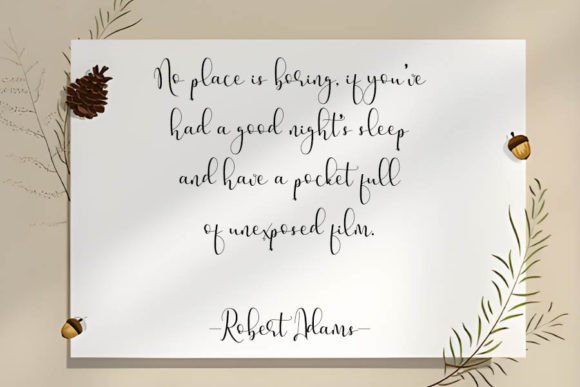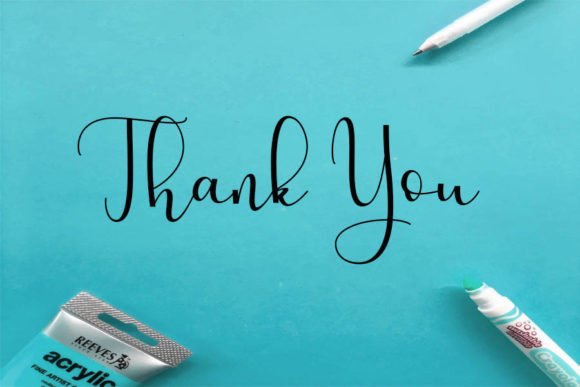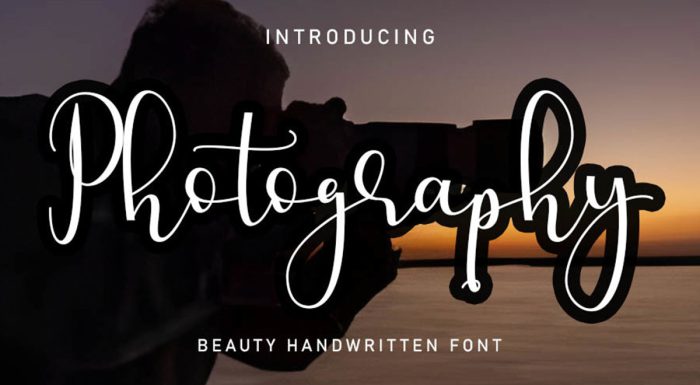
فونت Photography انگلیسی
فونت Photography، با خطوط نرم و خوشنویسی خاص خود، انتخابی ایده آل برای پروژه هایی است که نیازمند ظرافت و زیبایی هستند. این فونت، حسی از هنر عکاسی و ثبت لحظات ماندگار را به مخاطب القا می کند و به همین دلیل، برای طراحی لوگو، کارت ویزیت، وبسایت های مرتبط با عکاسی، آلبوم های عکس و حتی نوشته های کوتاه در شبکه های اجتماعی بسیار مناسب است.
یکی از ویژگی های برجسته Photography، خوانایی بالای آن است. با وجود ظرافت و پیچیدگی های خاص در طراحی حروف، این فونت در اندازه های مختلف به خوبی خوانده می شود و چشم را خسته نمی کند. این ویژگی، به ویژه در طراحی های دیجیتال که اندازه متن ممکن است متغیر باشد، اهمیت زیادی دارد. همچنین، تنوع وزن های مختلف این فونت، دست طراح را برای استفاده در موقعیت های گوناگون باز می گذارد. از متن های بولد برای عناوین گرفته تا متن های ظریف تر برای توضیحات، Photography به خوبی پاسخگوی نیازهای مختلف است.
البته باید به این نکته هم اشاره کرد که شاید این فونت برای متن های بسیار طولانی و کتابی مناسب نباشد، زیرا تمرکز آن بیشتر بر ایجاد جلوه ای خاص و هنری است تا خوانایی طولانی مدت. اما در عوض، اگر به دنبال فونتی هستید که به طرح هایتان روحی تازه ببخشد و آن ها را از سایرین متمایز کند، Photography گزینه ای بی نظیر است. تصور کنید نام یک آتلیه عکاسی با این فونت بر روی کارت ویزیت یا وبسایت آن نقش ببندد؛ این فونت به تنهایی می تواند گویای حرفه ای بودن و سلیقه خاص آن مجموعه باشد.
در نهایت، اگر به دنبال فونتی هستید که هم زیبایی خطوط خوشنویسی را داشته باشد و هم حسی مدرن و امروزی را منتقل کند، فونت Photography با خطوط نرم خود، انتخاب هوشمندانه ای خواهد بود. این فونت به شما کمک می کند تا پیام خود را به شکلی جذاب و تاثیرگذار به مخاطب منتقل کنید و طرح هایی خلق کنید که در ذهن ها ماندگار شوند.
| ⭐ توضیحات | عکاسی یک فونت دست نویس زیبا، با حروف نازک و بازیگوش است. چه از آن برای صنایع دستی، طراحی دیجیتال، ارائه ها یا ساخت کارت تبریک استفاده کنید، این فونت بدون توجه به مناسبت، این امکان را دارد که به فونت مورد علاقه شما تبدیل شود! |